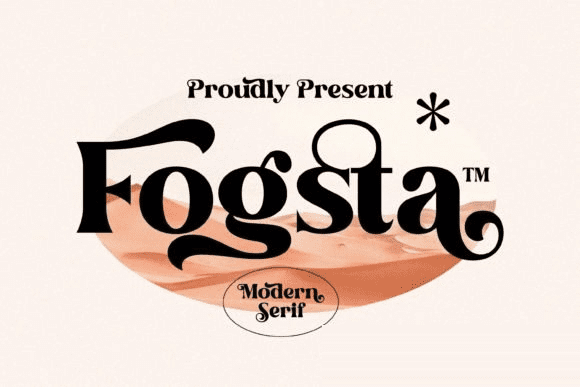
Название: Fogsta Font (2021)
Fogsta - современный, смелый и толстый шрифт с засечками.
Влюбитесь в его восхитительный стиль и используйте его для создания великолепных дизайнов!